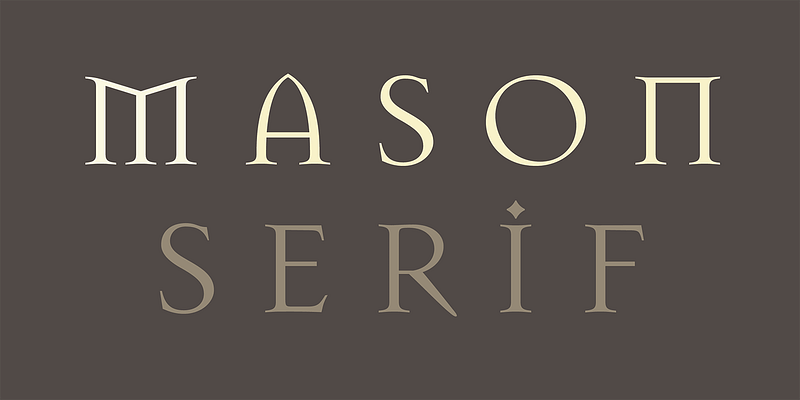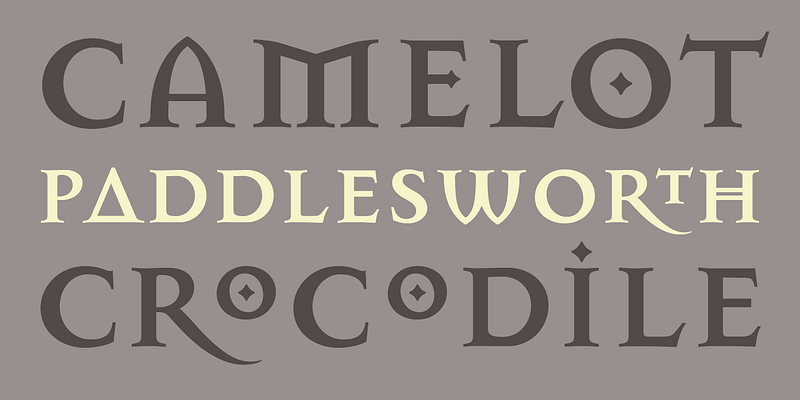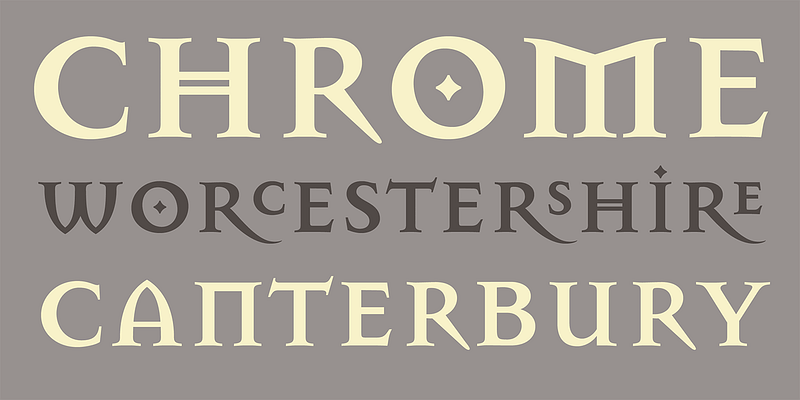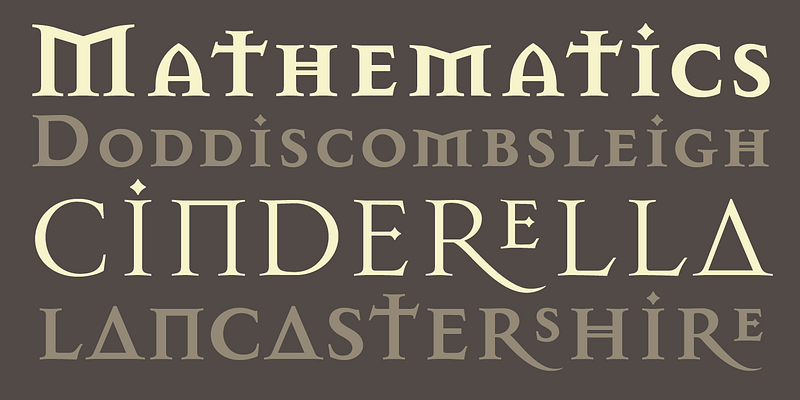
Mason ist sowohl in einer serifenbetonten als auch in einer serifenlosen Version erhältlich, und jedes Paket enthält drei Varianten: Regular, Alternate und Super, jeweils in zwei Strichstärken. Zusammen enthalten diese Schriften mehrere Varianten für jedes alphabetische Zeichen, jeweils in einer Großbuchstaben-, Kapitälchen- und Superskriptversion.
Das Design der Barnbrook wurde von den russischen Buchstabenformen des neunzehnten Jahrhunderts, der griechischen Architektur und den Bibeln der Renaissance beeinflusst. Die Schrift enthält auch viele Anspielungen auf die Populärkultur, die Politik und die Geschichte der Typografie. Die postmoderne Haltung von Mason ist unbestreitbar. Wie Jeffery Keedys Keedy Sans entstand Mason während der Explosion digitaler Schriften in den frühen 1990er Jahren, die beide Produkte der technologischen und kulturellen Einflüsse dieser Zeit waren.
Barnbrook nannte diese Schrift ursprünglich Manson (nach dem amerikanischen Serienmörder Charles Manson), „um die extremen gegensätzlichen Gefühle von Liebe und Hass, Schönheit und Hässlichkeit auszudrücken“. Nach der Veröffentlichung der Schrift geriet Emigre in die Kritik, einen Mörder zu verherrlichen, und beschloss, den Namen in Mason zu ändern, da die Buchstabenformen auch an die Arbeit von Steinmetzen, die Symbolik der Freimaurer und heidnische Ikonografie erinnern.